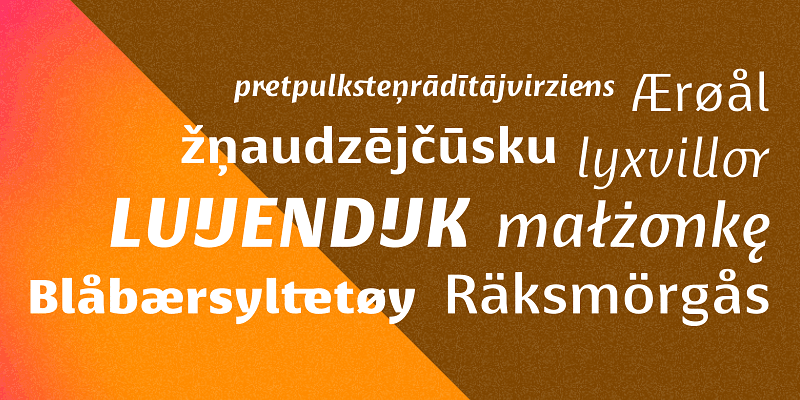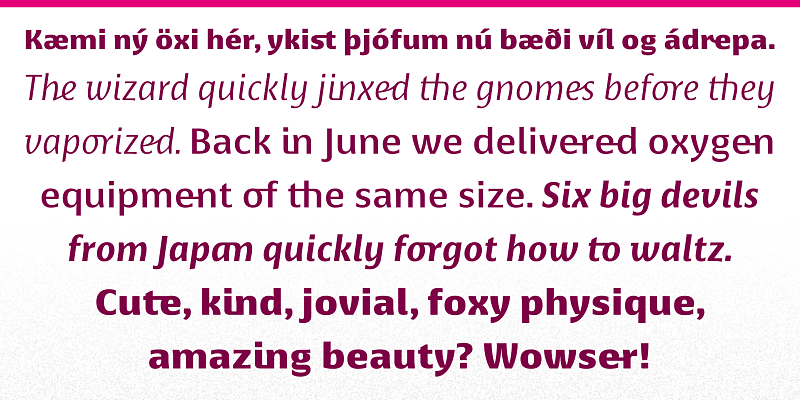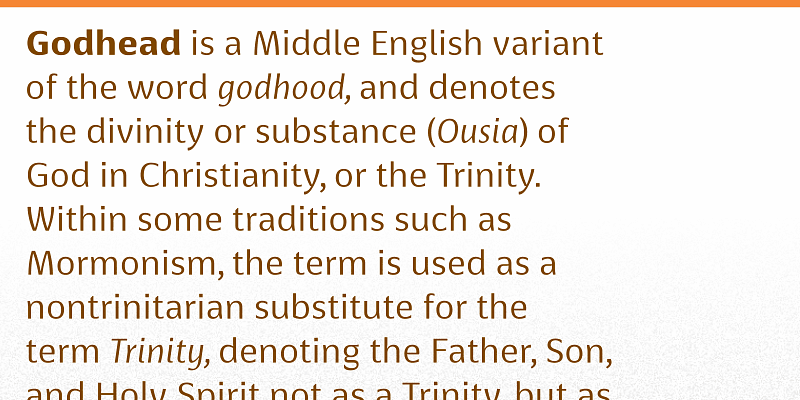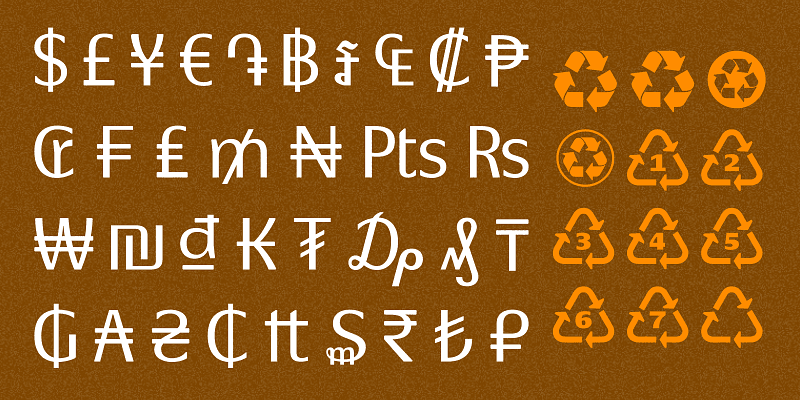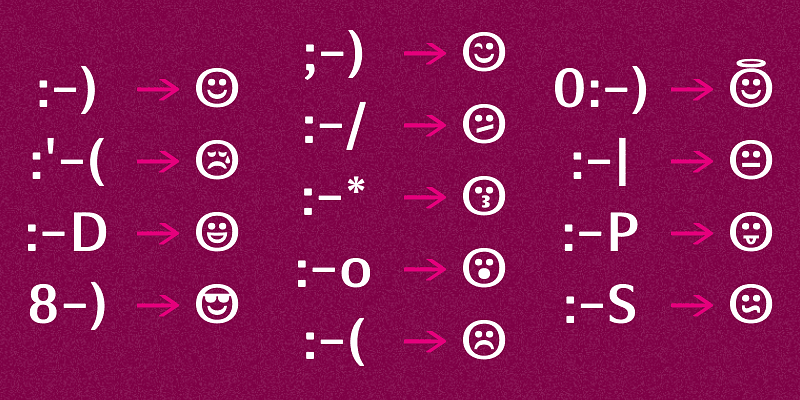
Basel Neue ist eine gut lesbare, diskrete Sans Sans mit Dickenvariation und humanistischem Touch, mit vielen nützlichen Glyphen und Funktionen – Emoticons, Währungs-/Recyclingsymbole, Dutzende von Ligaturen und mehr.